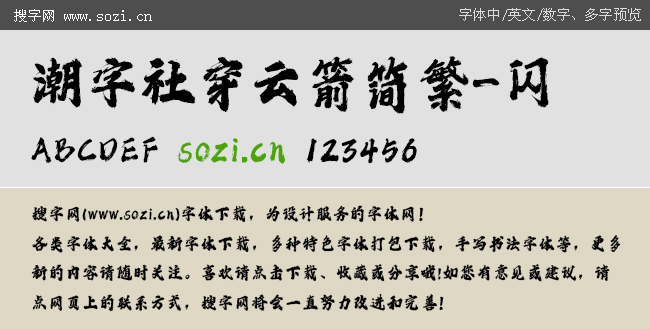
潮字社穿云箭簡繁-閃
搜字網(wǎng)提供一款潮字社穿云箭簡繁-閃中文字體下載,潮字社穿云箭簡繁-閃是一款非常獨(dú)特的個(gè)性毛筆藝術(shù)字體,這款字體字形大氣灑脫,獨(dú)具一格,筆畫圓潤,有張力,筆畫之間粗細(xì)對比強(qiáng)烈,飛白與牽絲增添了不少活力。適合應(yīng)用于藝術(shù)設(shè)計(jì)、平面宣傳設(shè)計(jì)、網(wǎng)頁設(shè)計(jì)等領(lǐng)域等應(yīng)用。。(本字體為個(gè)人非商用版,商用請聯(lián)系作者購買授權(quán)。官方網(wǎng)址:http://www.reeji.com 聯(lián)系方式:021-58597892)